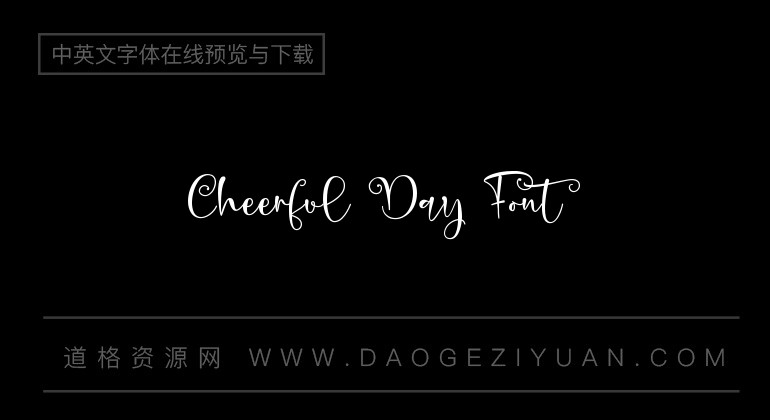
Cheerful Day Font
Cheerful Day Font是一种手写风格的字体,具有轻快、欢快、温馨的特点。该字体由字母、数字和标点符号组成,每个字符都有自己独特的风格和特点。该字体适合用于卡片、海报、标志、书籍封面等设计中,可以让设计作品更加生动、有趣、个性化。 Cheerful Day Font是一款免费字体,可以在许多字体网站上免费下载和使用。它支持多种语言,包括英语、西班牙语、法语、德语等,可以满足不同用户的需要。它的设计风格独特,让文字变得更加有趣和富有表现力,适合用于轻松、欢快、温馨的场合。
Cheerful Day Font是一款非常不错的手写艺术字体,具有很好的视觉感,适合于文化类的宣传设计、商业类品牌的广告和产品包装设计以及个性化文字排版等较多场景。